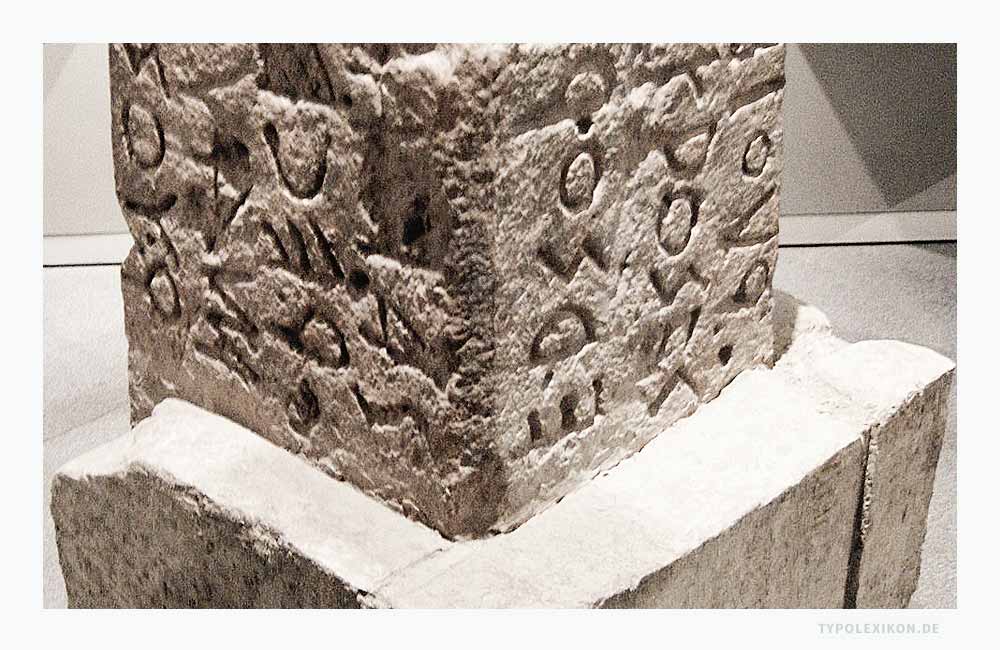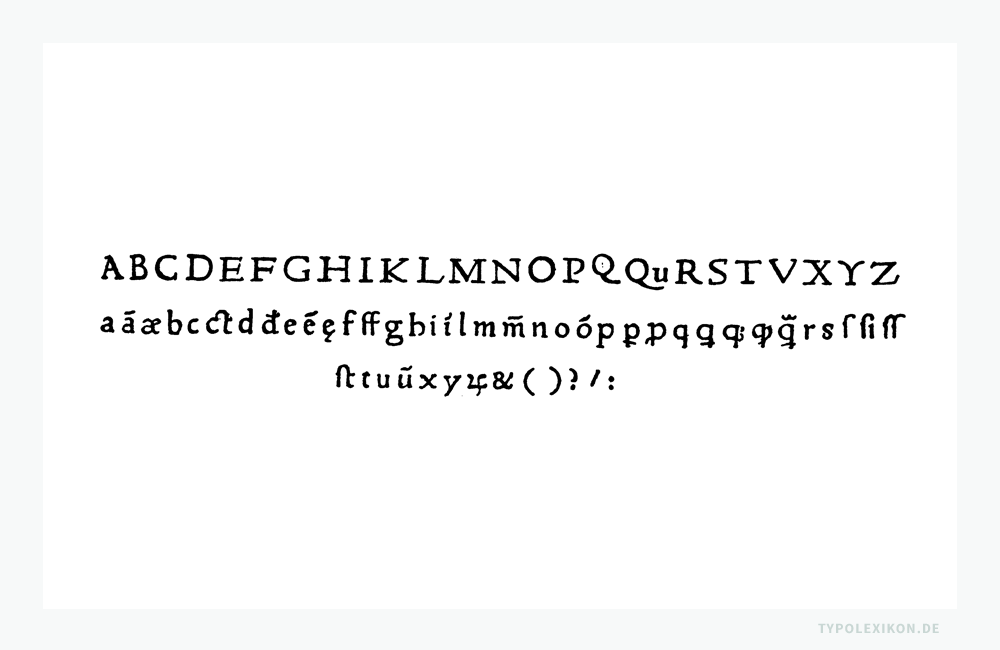
Schriftgeschichte
Schrift ist eine der ältesten Kulturtechniken der Menschheit. Sie wird heute als Medium zur Kommunikation und als eine Technologie zur Weitergabe und Archivierung von Wissen verstanden. Schriftsysteme sind autonom an vielen Orten der Welt entstanden. Archaische Vorstufen unserer Buchstaben bzw. Alphabetschrift finden sich in Höhlen- und Wandmalereien aus dem Paläolithikum sowie in Form von prähistorischen Kerb- und Zählzeichen in Holz, Stein und Knochen bzw. als Einritzungen auf Kultgegenständen. Zeichensysteme für Zahlen und Zahlenbegriffe sind in der Geschichte der Menschheit schon bereits 30.000 bis 25.000 v. Chr. zu finden. 1) 2)
Eine monogenetische Schriftkultur mit einem einzigen Ursprungsort und einer kontinuierlichen Verbreitungslinie, wie sie leider immer noch in typografischen Lehrbüchern propagiert wird, existiert nicht. Neueste Erkenntnisse untermauern die These von einer Schriftpolygenese in den folgenden Regionen: Südosteuropa 5500 v. Chr., Altägypten 3500 v. Chr. (Hieroglyphen), Mesopotamien 2700 v. Chr. (sumerische Keilschriften), Industal 2300 v. Chr. (Indien), China 1900 v. Chr. und Mittelamerika 1000 v. Chr. (Schrift der Olmeken). 3) 4) 5)
Die jeweilig praktizierte Schreib- oder Drucktechnik war ebenso wie das Trägermaterial bestimmend für die Ästhetik eines Schreibstils bzw. einer Schriftart. Vor der Erfindung der Typografie dienten diverse spitze Ritzwerkzeuge, Meißel, Holzgriffel, Rohrpflanzen, Federkiele von Vögeln sowie metallene Griffel und Federn als Schreibinstrumente (siehe auch Kalligraphie). Mit der Erfindung der Typografie kamen aus Metallen hergestellte Stahlstäbchen, Stichel zum Gravieren und Stechen (Hoch- und Tiefdruck), sowie Pinsel, Stifte, Lineale und Zirkel (Lithographie) hinzu.
Die ursprünglichen Trägermaterialien waren Stein, Knochen, Holz, Leder, Blätter, Ton, Wachs, Holz, Metall, Stoff, Papyrus, Pergament, Papier und Tapabast; seit der Prototypografie wird nahezu ausschließlich Papier verwendet.
Schrift war bis zu den Anfängen der Typografie, also rund 6800 Jahre lang, ausschließlich ein Instrument der sozialen und politischen Elite; der innovative und kreative Umgang mit dem Medium Schrift blieb bis in die Mitte/Ende des 20. Jahrhunderts patriarchal dominiert.
Durch den gegenwärtigen Wandel von der materiellen Schrifttechnologie hin zu virtuellen multimedialen Informationstechnologien, erlebt unsere Schriftkultur einen noch niemals da gewesenen Strukturwandel, der unsere Schreib-, Lese- und Betrachtungsgewohnheiten in den nächsten Jahren nachhaltig verändern wird.
Chronographie
5300 v. Chr. | Das erste mutmaßliche Schriftsystem stammt aus Europa aus der Zeit um 5500 v. Chr. Es handelt sich hierbei um Inschriften auf Kultgegenständen einer südosteuropäischen Donauzivilisation, eingeritzt in den Tontafeln von Tartaria im rumänischen Transsylvanien. 6)
3320 v. Chr. | Die altägyptischen Hieroglyphen aus dem Königsfriedhof von Abydos (3320–3150 v. Chr.) und die sumerische Keilschrift aus Mesopotamien (um 2600 v. Chr.) sind die ältesten Zeugnisse für die Schriftkultur im »Alten Orient«.
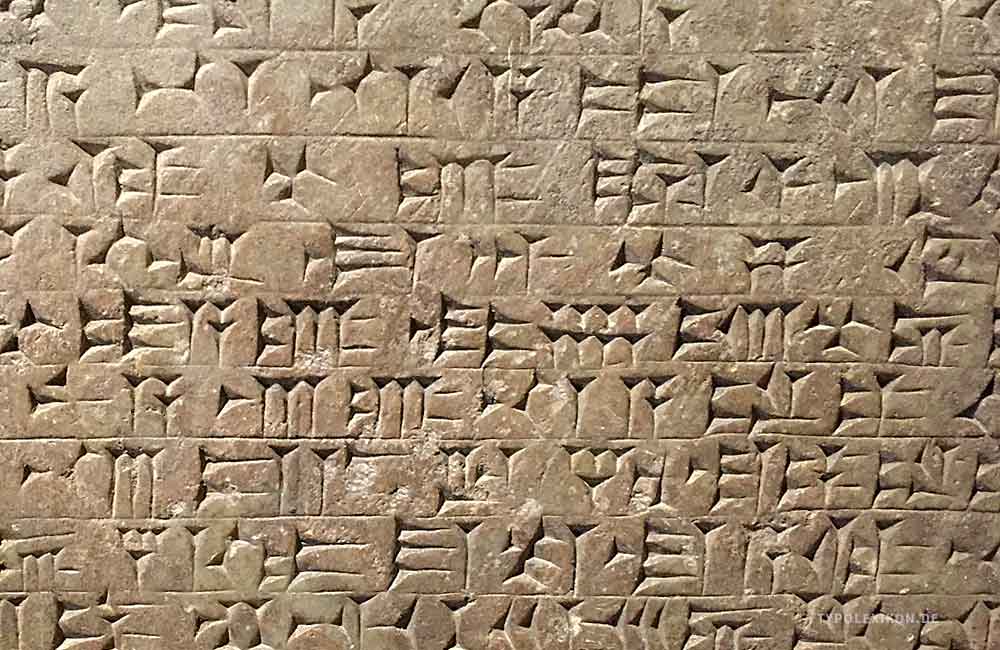
2500 v. Chr. | Um 2500 v. Chr. lebten die südosteuropäischen Zeichenformen im altkretischen Schriftsystem Linear A wieder auf.
2000 v. Chr. | Der Einfluss dieser altminoischen Linearschrift A auf die am Festland gebräuchliche mykenisch-griechische Linear B ist neben Zypern auch über die syrische Hafen- und Handelsstadt Ugarit nachzuweisen, die um 1800 v. Chr. zu einer Art Schmelztiegel für die unterschiedlichsten orientalischen Schriftsysteme wurde.
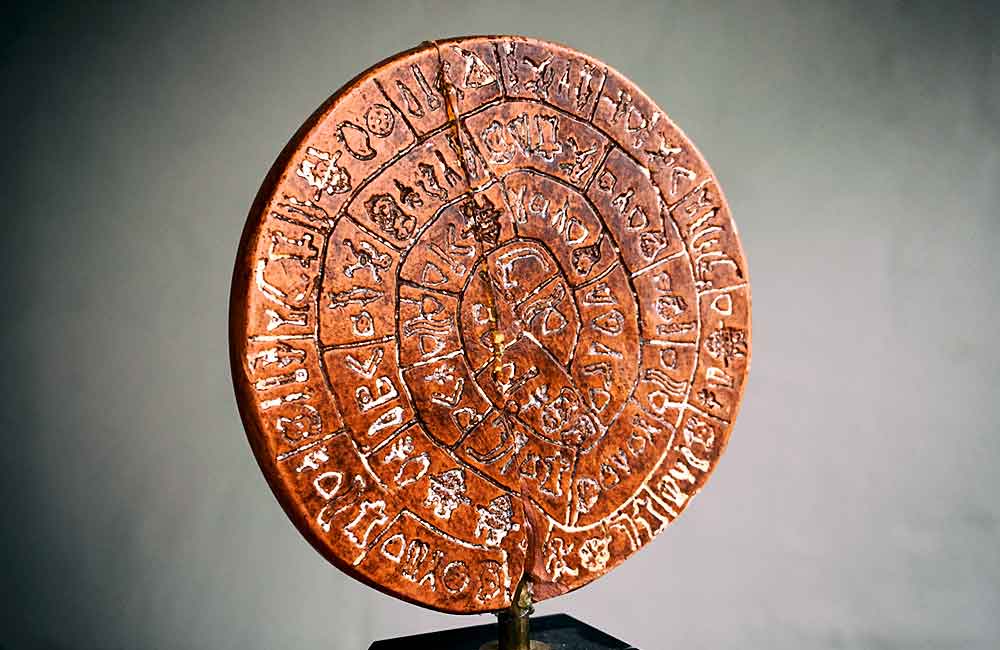
1700 v. Chr. | Parallel dazu entwickelte sich auf Kreta auch eine autarke Hieroglyphenschrift, in der das bekannteste Schriftdenkmal der minoischen Zivilisation mutmaßlich abgefasst wurde, der Spiraltext auf dem Diskos aus dem Palastarchiv von Phaistos – welcher allerdings bis heute nicht entziffert werden konnte. Dieses auf etwa 1700 v. Chr. datierte Schriftdokument ist herstellungstechnisch betrachtet das älteste Druckwerk der Kulturgeschichte, denn die Hieroglyphenzeichen wurden mit Stempeln in den weichen Ton gepresst, bevor der Diskos hart gebrannt wurde.
Alphabet
1500 v. Chr. | Der rege Kulturaustausch im Nahen Osten führte dazu, dass aus der in den regionalen altsemitischen Sprachen üblichen sumerischen Keilschrift Mesopotamiens in Ugarit im 15. Jahrhundert v. Chr. ein reines Buchstabenalphabet selektiert wurde, auf dessen Entstehungsprozess neben den erwähnten altägäischen Schriftsystemen auch hieroglyphische und hieratische Varianten der ägyptischen Schrift, die Sinai-Schrift und die syllabische Byblos-Schrift eingewirkt hatten. Vom ugaritischen Keilschriftalphabet ist ein Abecedarium mit 27 Hauptzeichen überliefert, das dieselbe altsemitische Ordnung der Konsonanten aufweist, wie das spätere phönizische Alphabet. Nach der Zerstörung Ugarits durch die so genannten Seevölker um 1200 v. Chr. wurde die phönizische Version zur wichtigsten Schriftart der Küstenregion.
Als eine der bedeutendsten semitischen Kultursprachen des Altertums wurde das Phönizische im Frühstadium seiner Schriftlichkeit in drei Schriftsystemen geschrieben: in der Byblos-Silbenschrift, im ugaritischen Keilschriftalphabet und schließlich im 22 Buchstabenzeichen umfassenden phönizischen Alphabet. Von dieser »Phoinikeia grammata« stammt auch das deutsche (lateinische) Alphabet ab. 7)
1000 v. Chr. | Eine um 1050 v. Chr. entstandene Inschrift auf dem Sarkophag des Königs Ahiram aus Byblos zeigt die klassische Form dieser Schrift, die sich durch die intensiven Handelsbeziehungen der Phönizier und das interkulturelle Netz, das sie gemeinsam mit den Karthagern aufgebaut hatten, rasch über den gesamten Mittelmeerraum ausbreitete. Die mutmaßlich älteste proto-kanaanitische Schrift (Vorgänger des hebräischen Alphabets) könnte aus dem Jahre 1000–975 v. Chr. stammen, woraufhin eine 15 mal 15 Zentimeter grosse Tonscherbe mit einer fünfzeiligen Inschrift deutet, die im Juli 2008 bei Ausgrabungen in Hirbet Keijafa, nahe der Stadt Beit Schemesch, im Süden Israels gefunden wurde. 8)